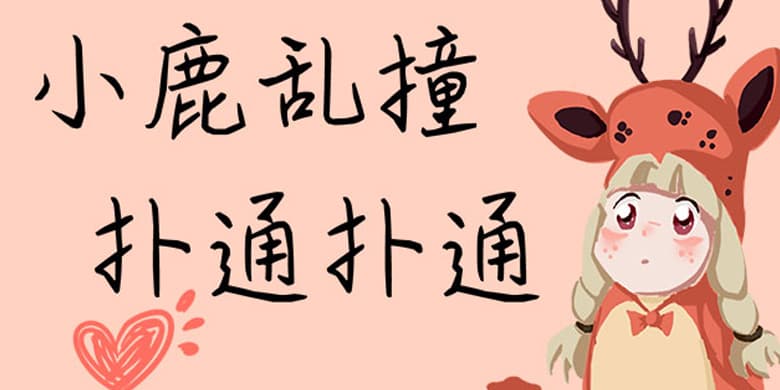
品牌:方正手迹设计师:宋昱东发行时间:2020字库编码:简繁扩展(GBK)分类:常规书写·硬笔字体属性:精品字
该字最初给人的感觉是温暖与内敛,笔画设计上无锋芒,似在讲一个故事,尾尾道来。构字方式中正平各,有比较良好的阅读体验。适用于文艺类的书刊、品牌广告和产品包装设计,以及社交网络的个性化用字。